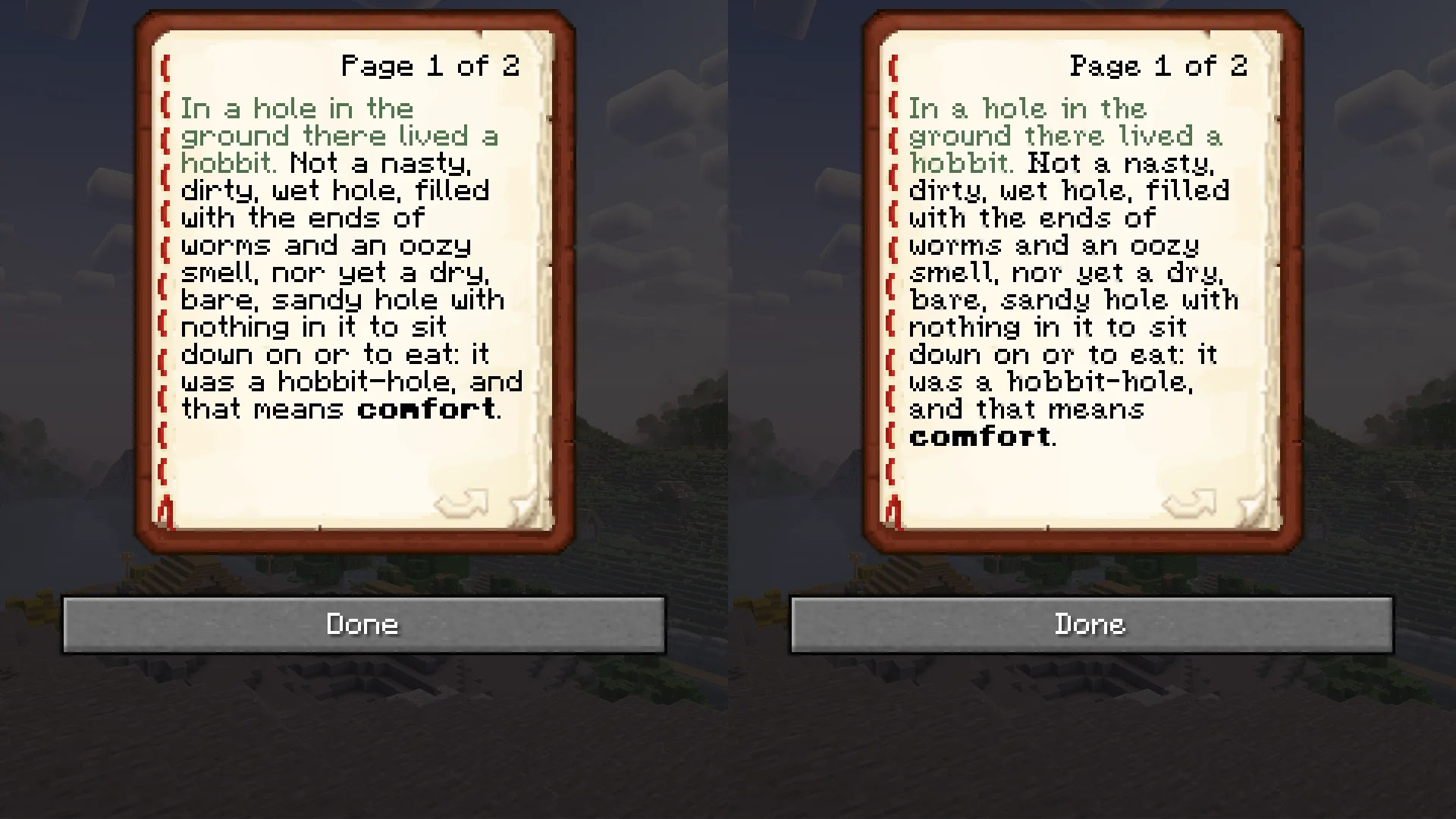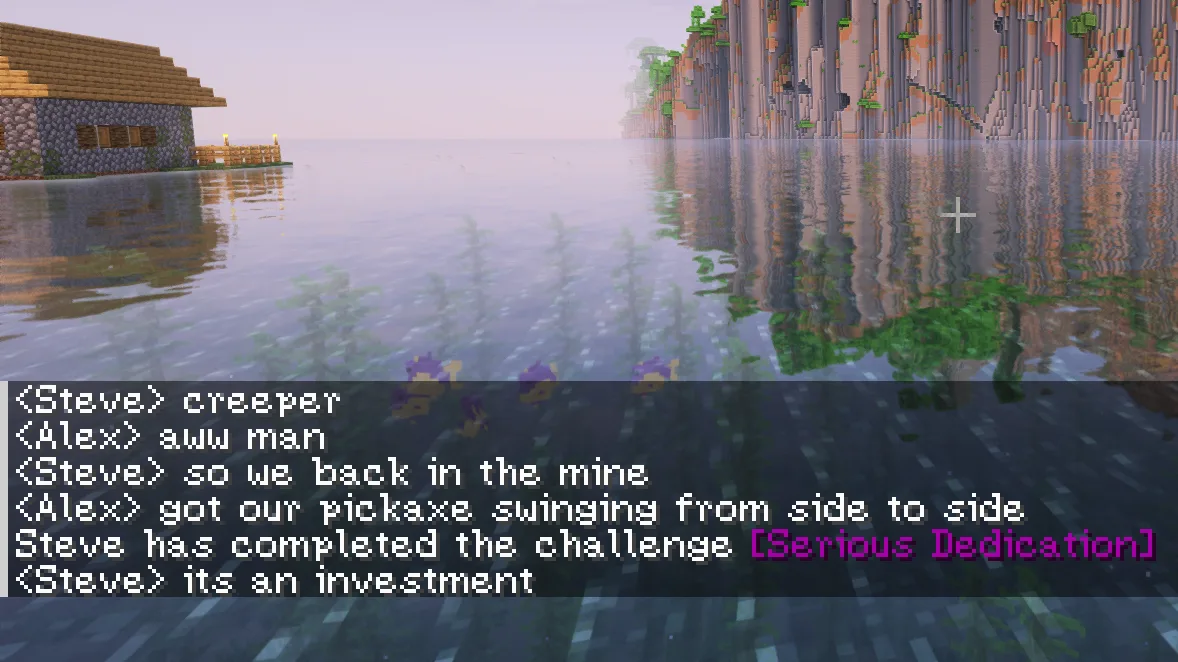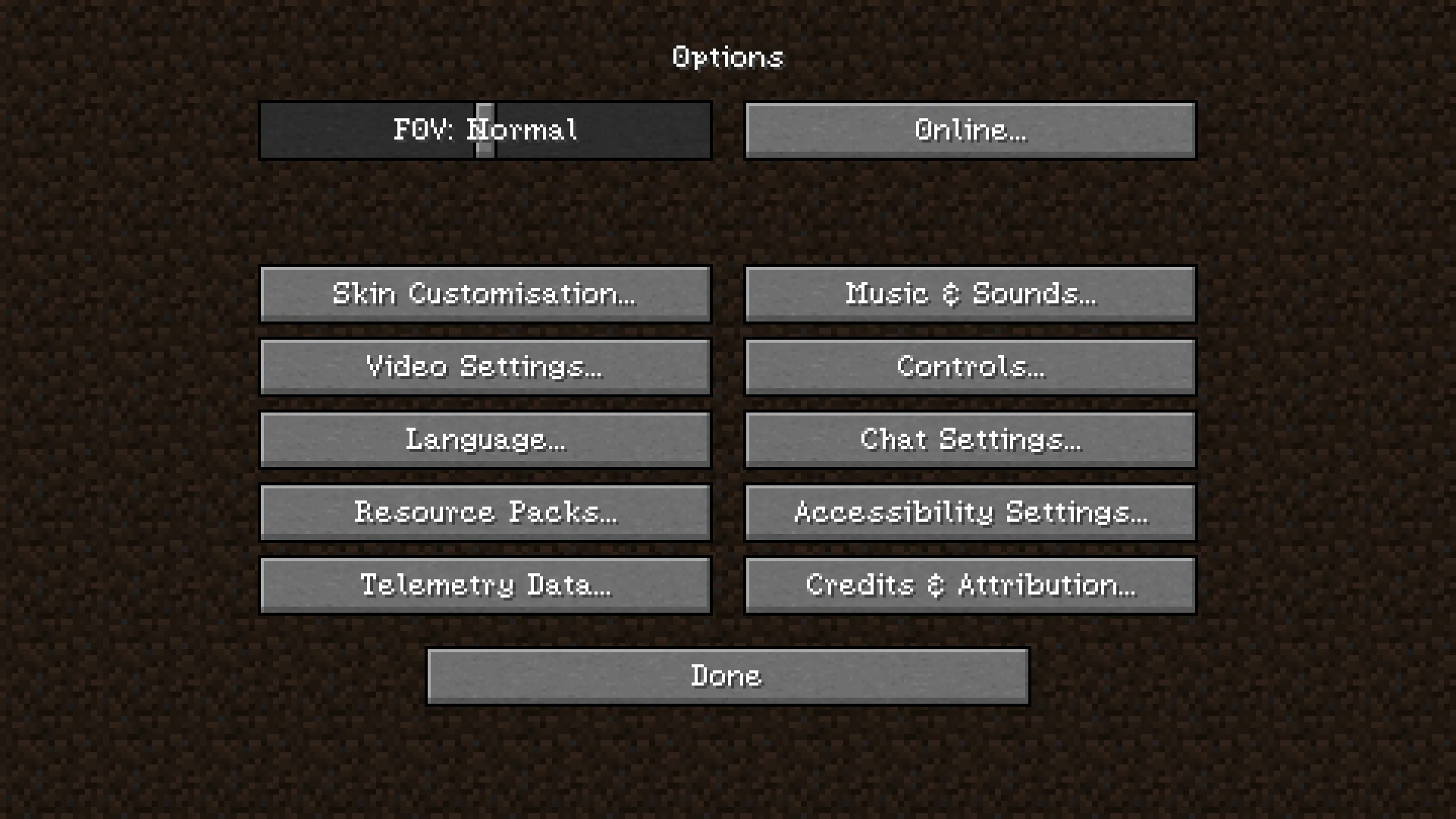
(Bee's) Serified Font
Ресурспак перерабатывает шрифт Minecraft, придавая тексту фэнтезийный и средневековый вид с улучшенной читаемостью.
Этот ресурспак полностью изменяет шрифт Minecraft, делая текст более фэнтезийным и соответствующим магической и средневековой атмосфере игры. Шрифт стал более человечным и удобочитаемым.
В шрифте используются полупрозрачные пиксели для сглаживания, что является уникальной особенностью среди ресурспаков. Однако результаты рендеринга могут различаться в зависимости от системы.
Ресурспак не поддерживает диакритические знаки и акценты. Совместимость с модами может быть неидеальной: в некоторых случаях шрифт может отображаться некорректно, особенно с полупрозрачными пикселями.